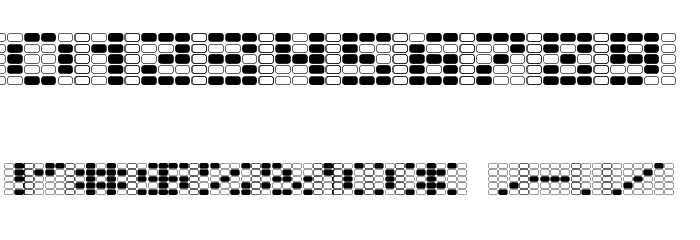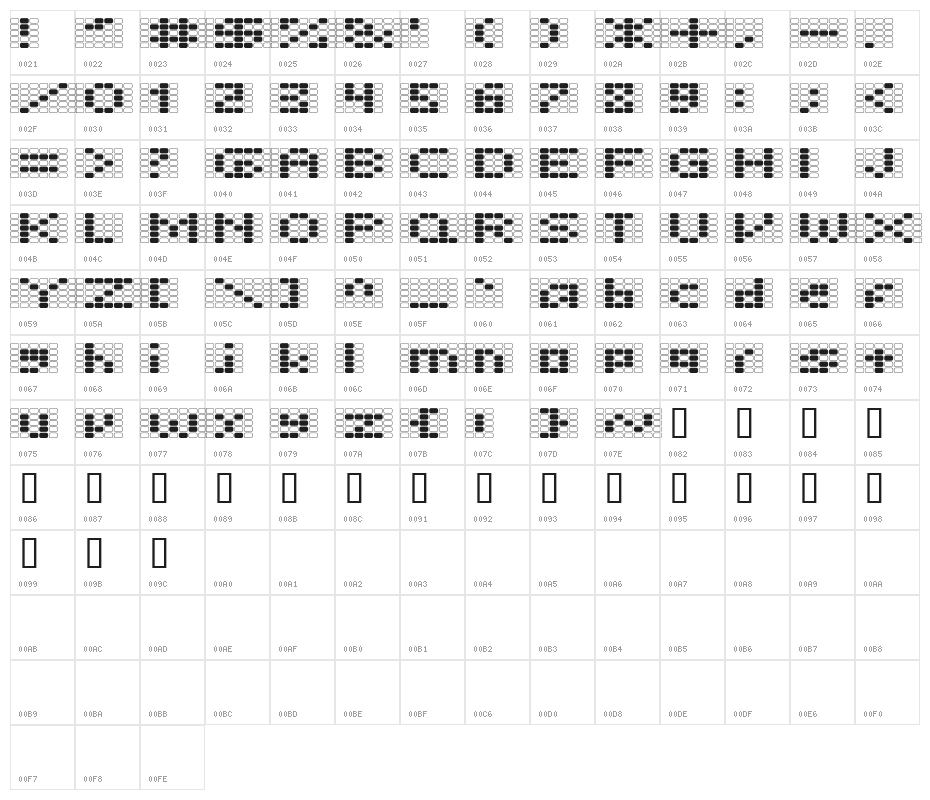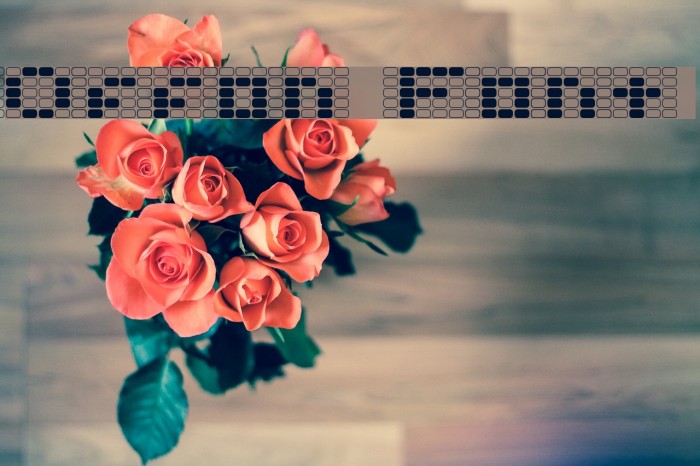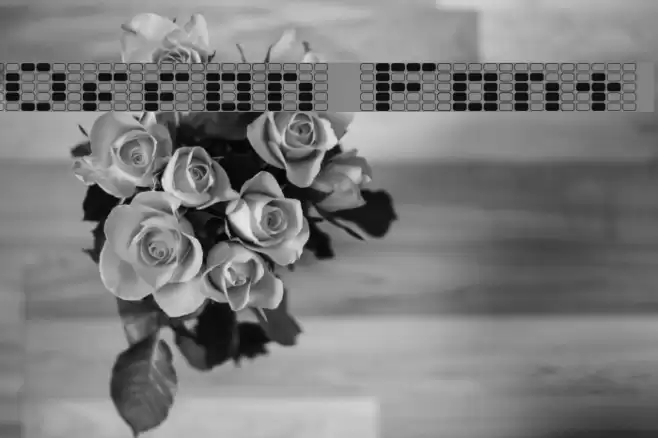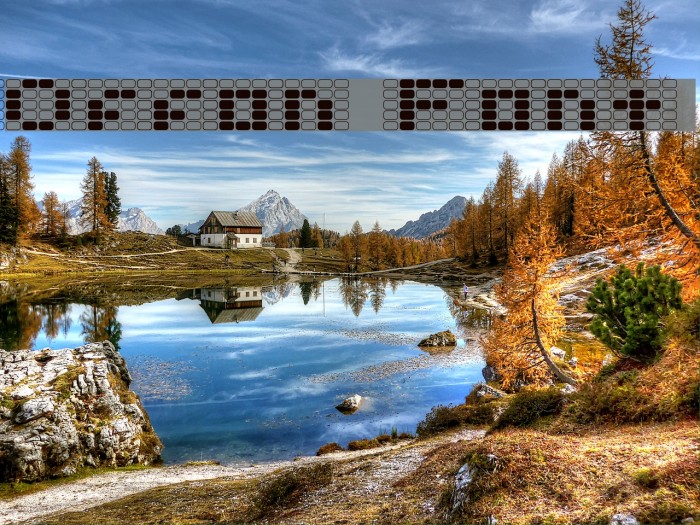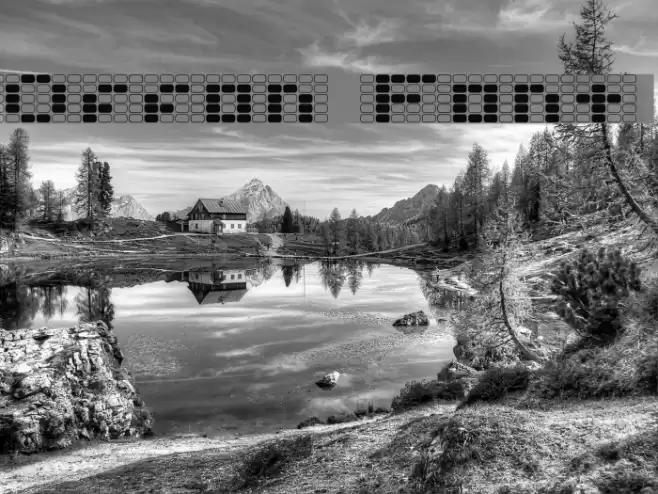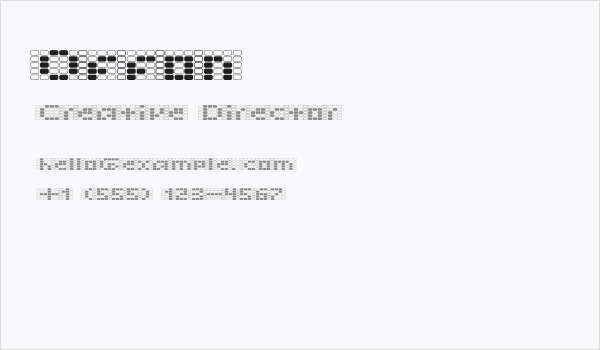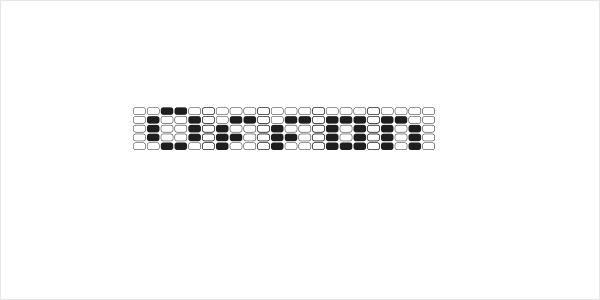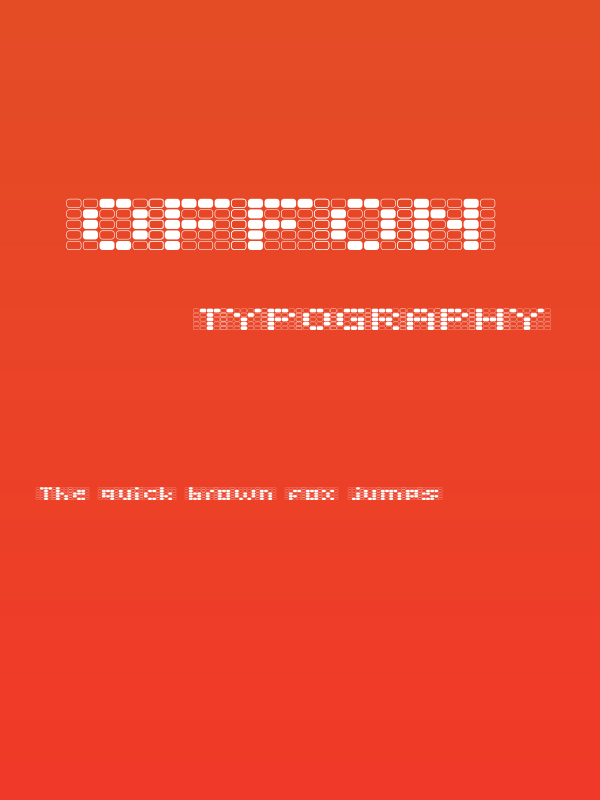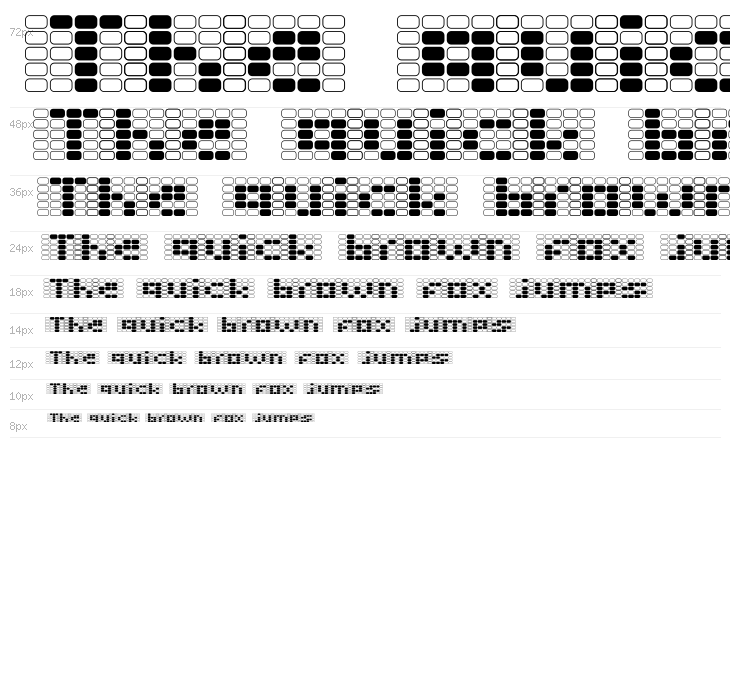
Offon Font
| カテゴリ | Pixel |
| 用途 | Headlines, Logos, Digital interfaces |
| おすすめプロジェクト | Ideal for digital art, retro-themed designs, tech-related branding, and video game interfaces. |